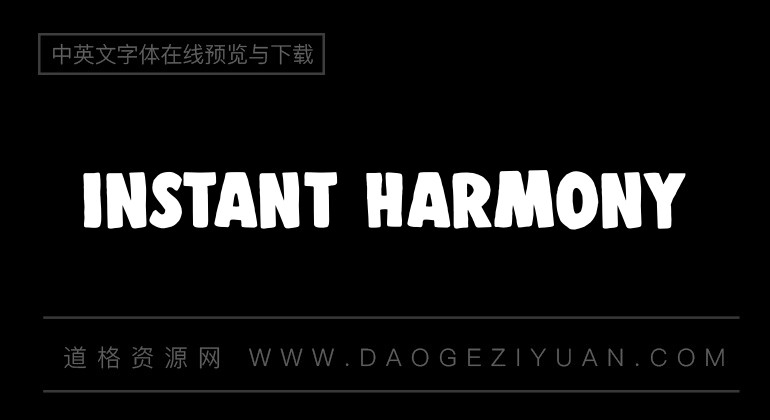
Instant Harmony
? Instant Harmony 字体是一款新颖的英文字体,它采用现代设计理念,结合传统的美感,构建出极具灵动感的字体。它的字母形状紧凑,节奏自然,线条流畅,表达力强,给人以柔和、温暖的感觉,非常适合用于商业广告、网页设计、报纸杂志、书籍封面等领域。
Instant Harmony是一款非常不错的手写艺术字体,具有很好的视觉感,适合于文化类的宣传设计、商业类品牌的广告和产品包装设计以及个性化文字排版等较多场景。